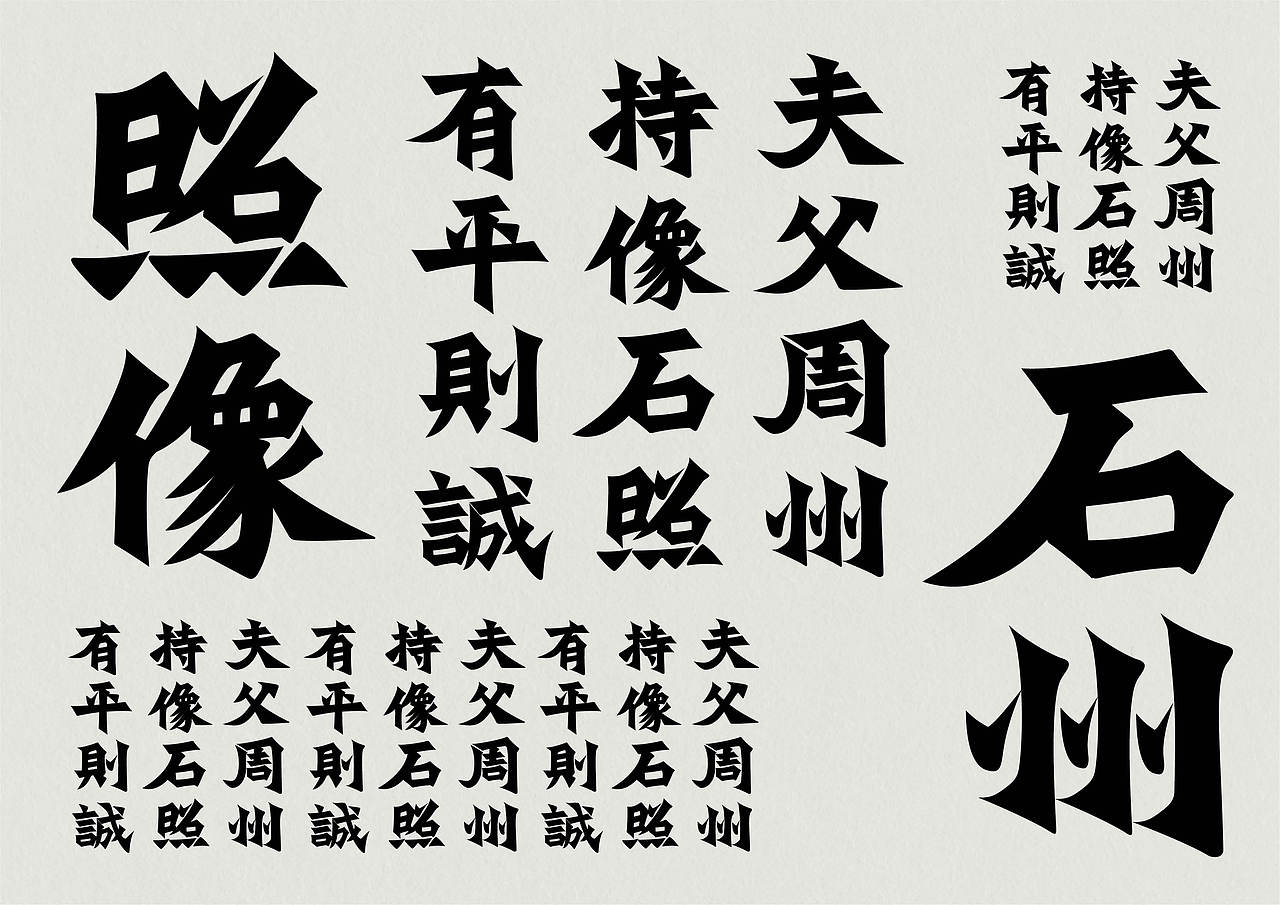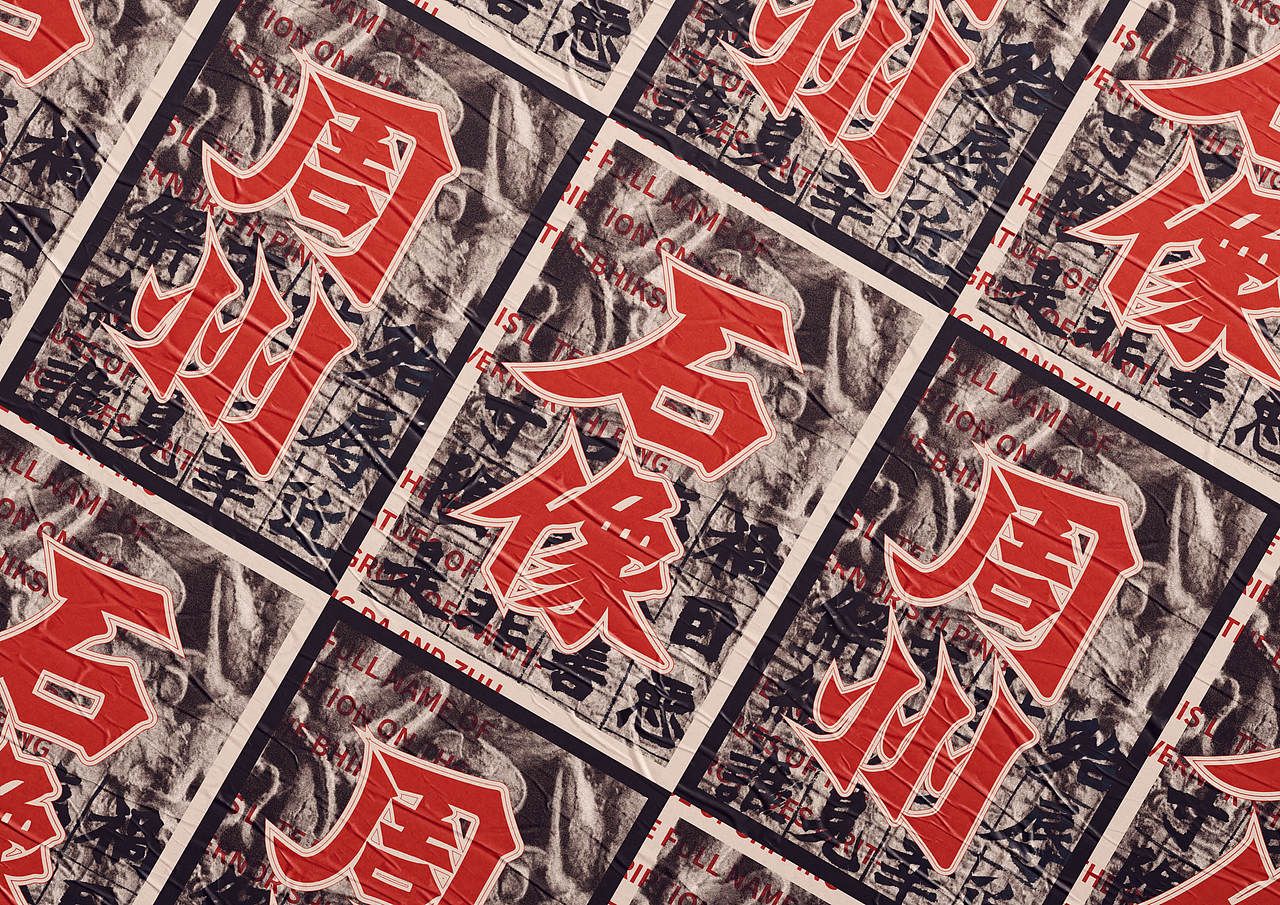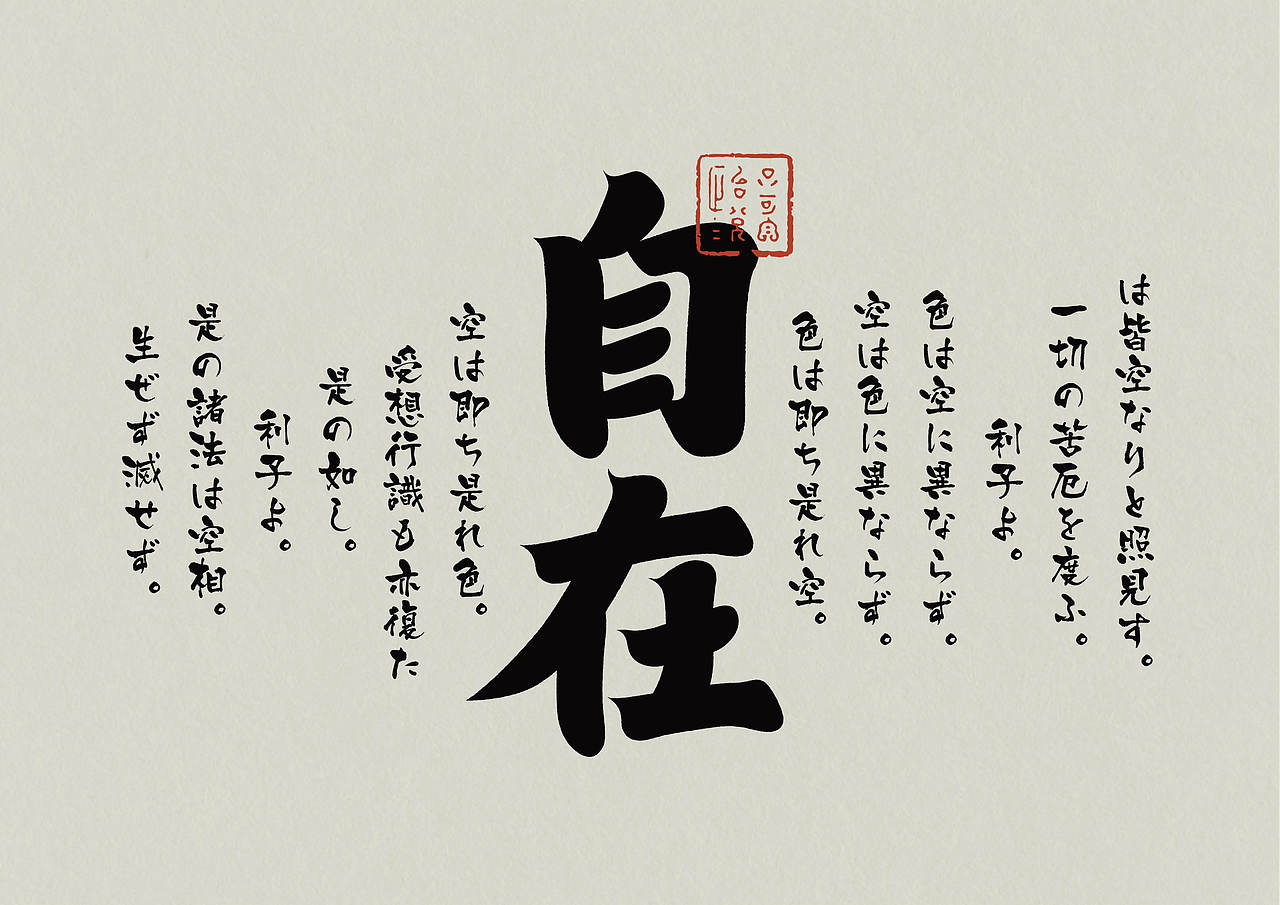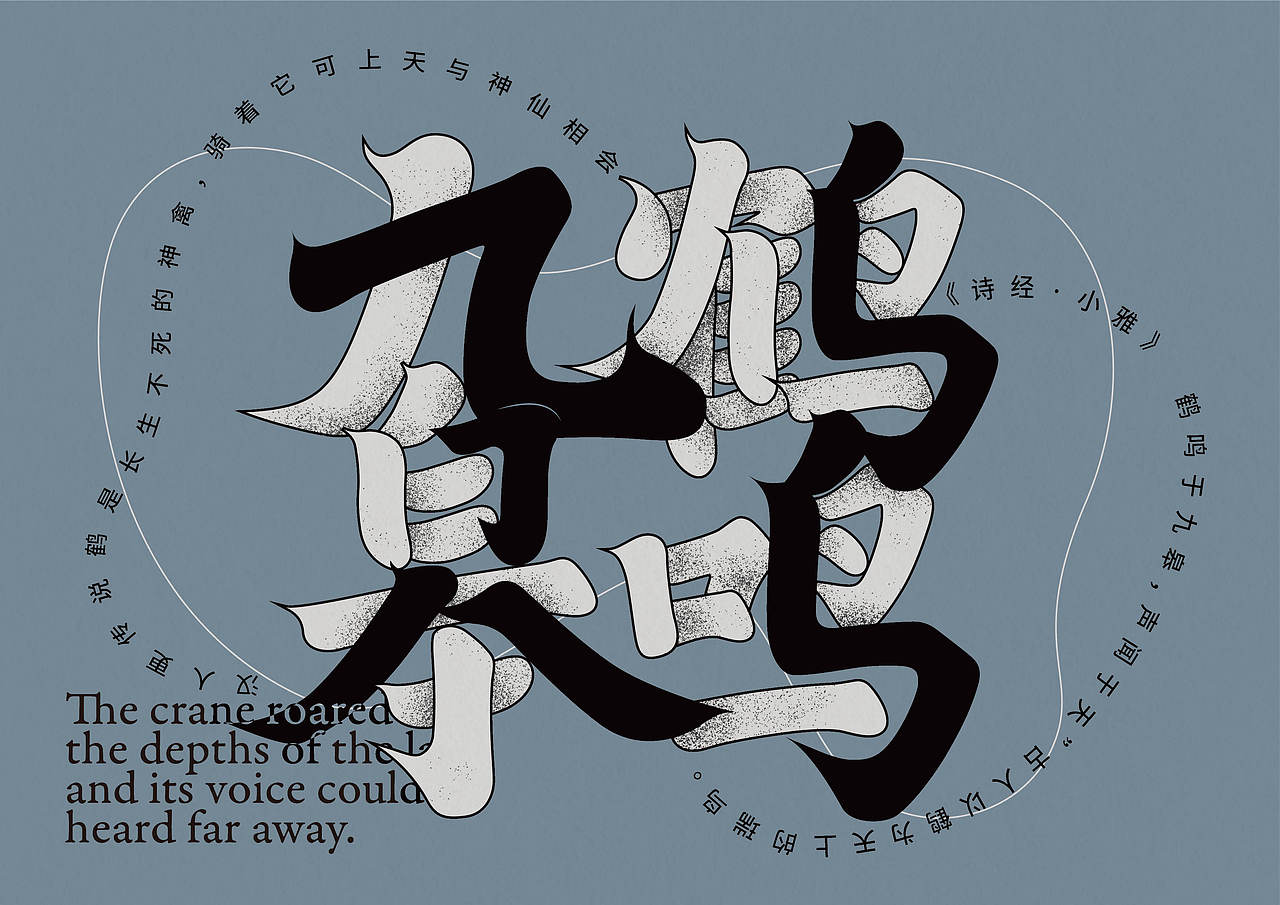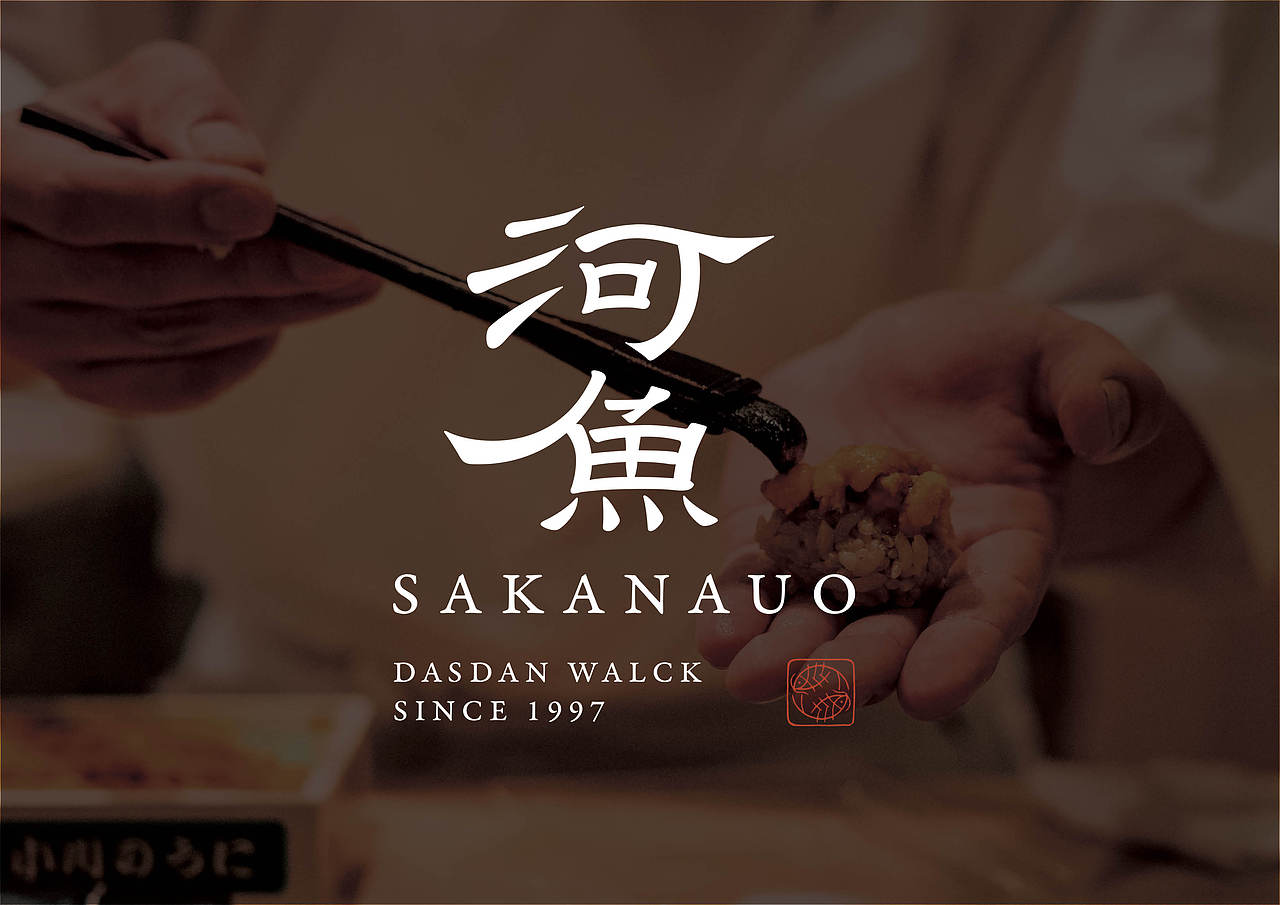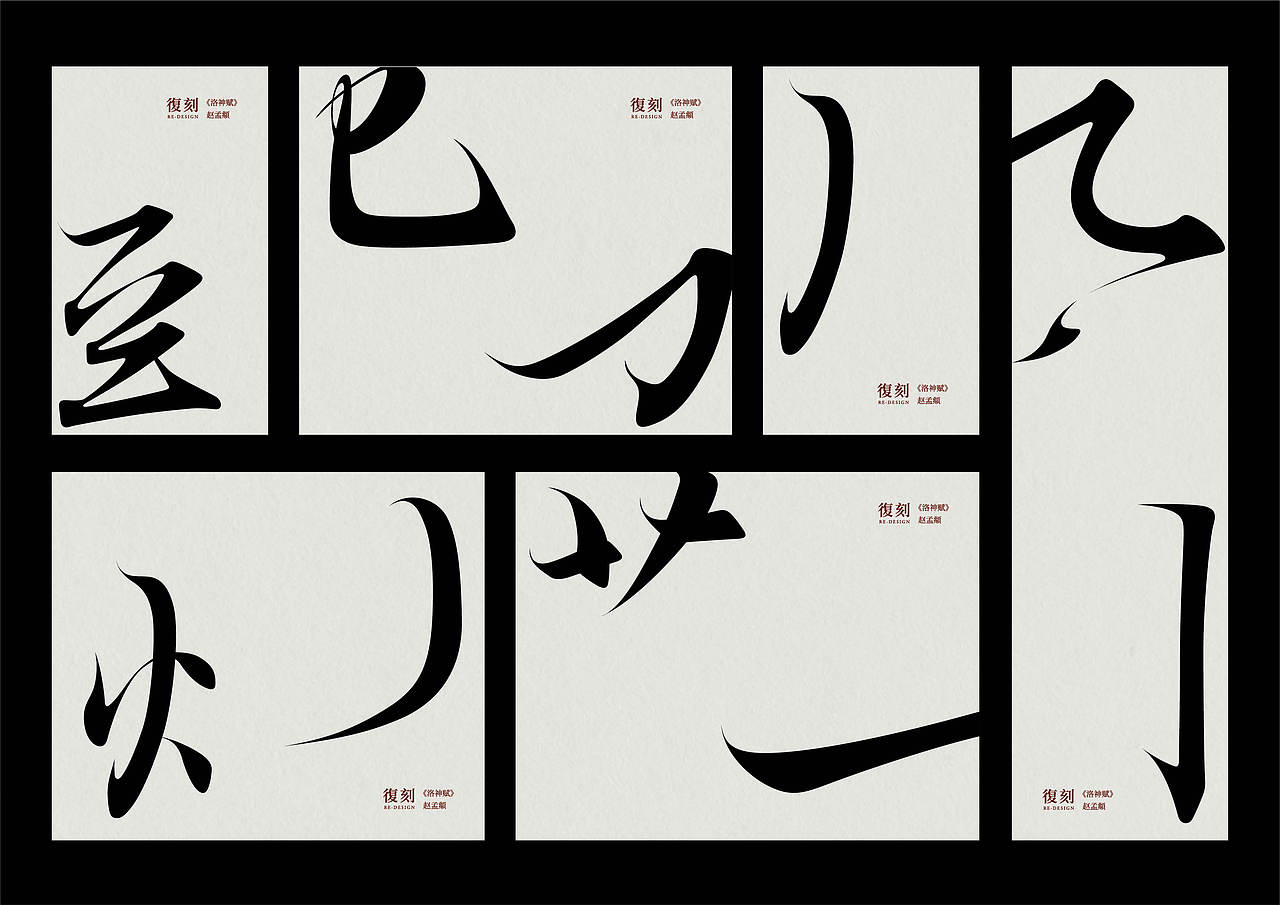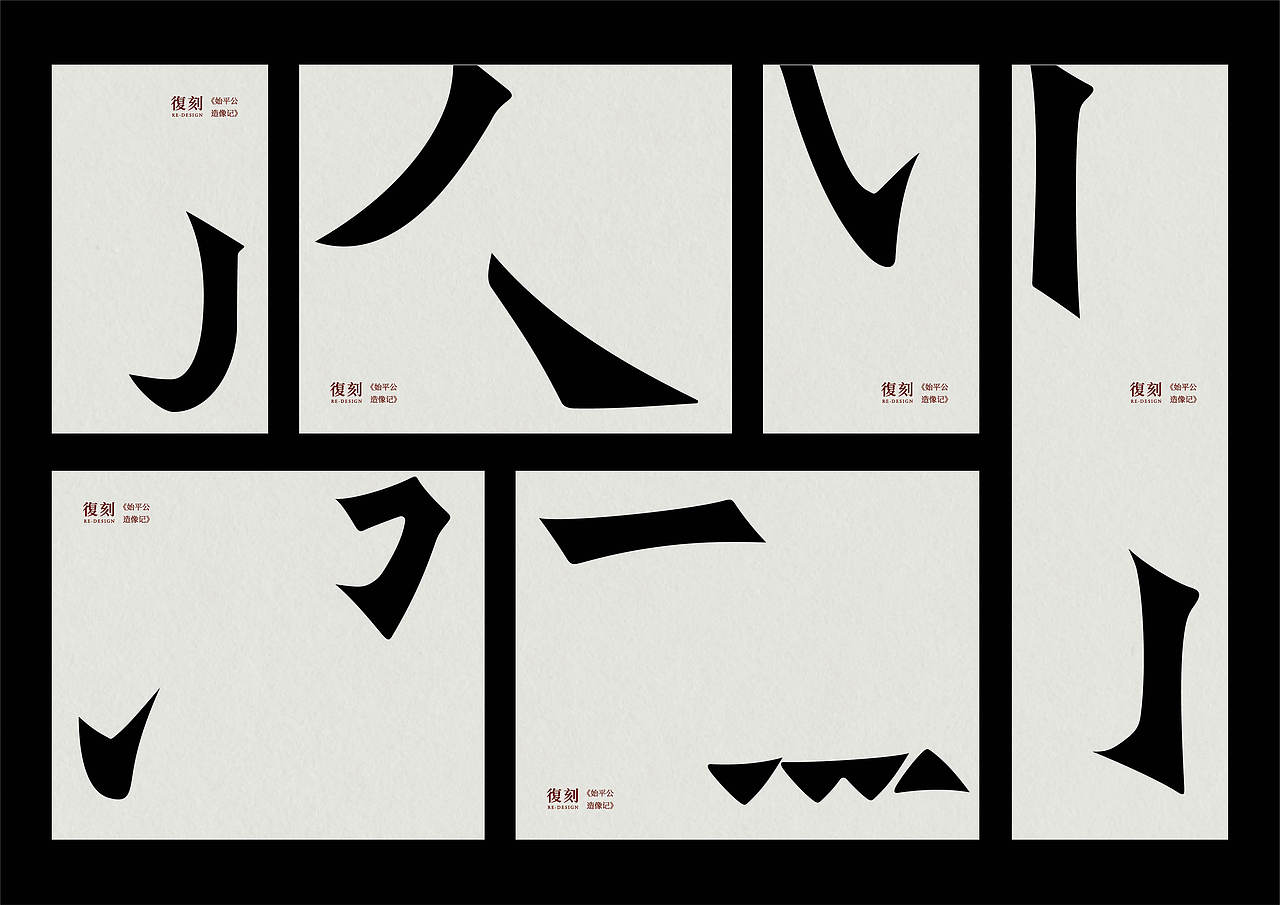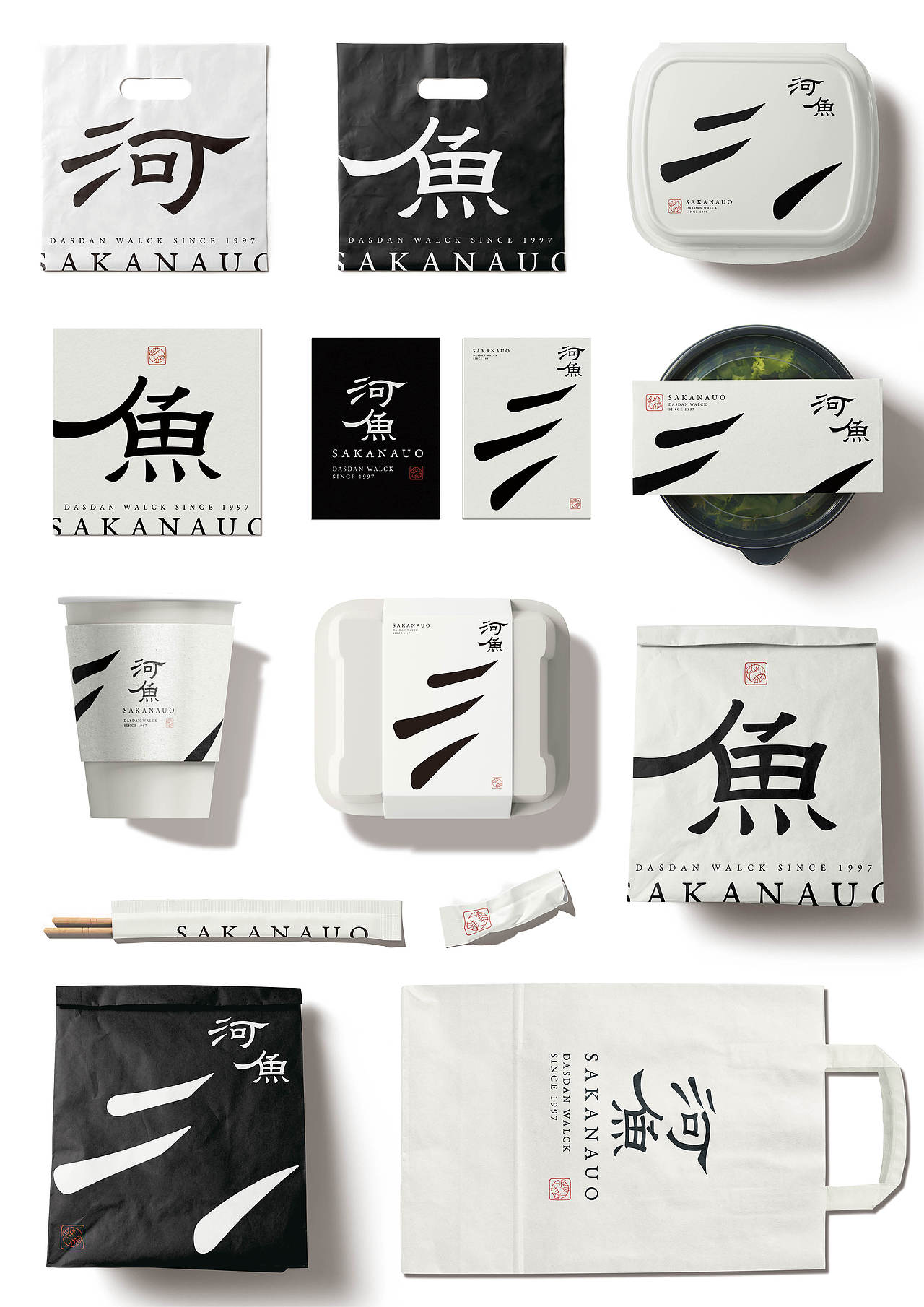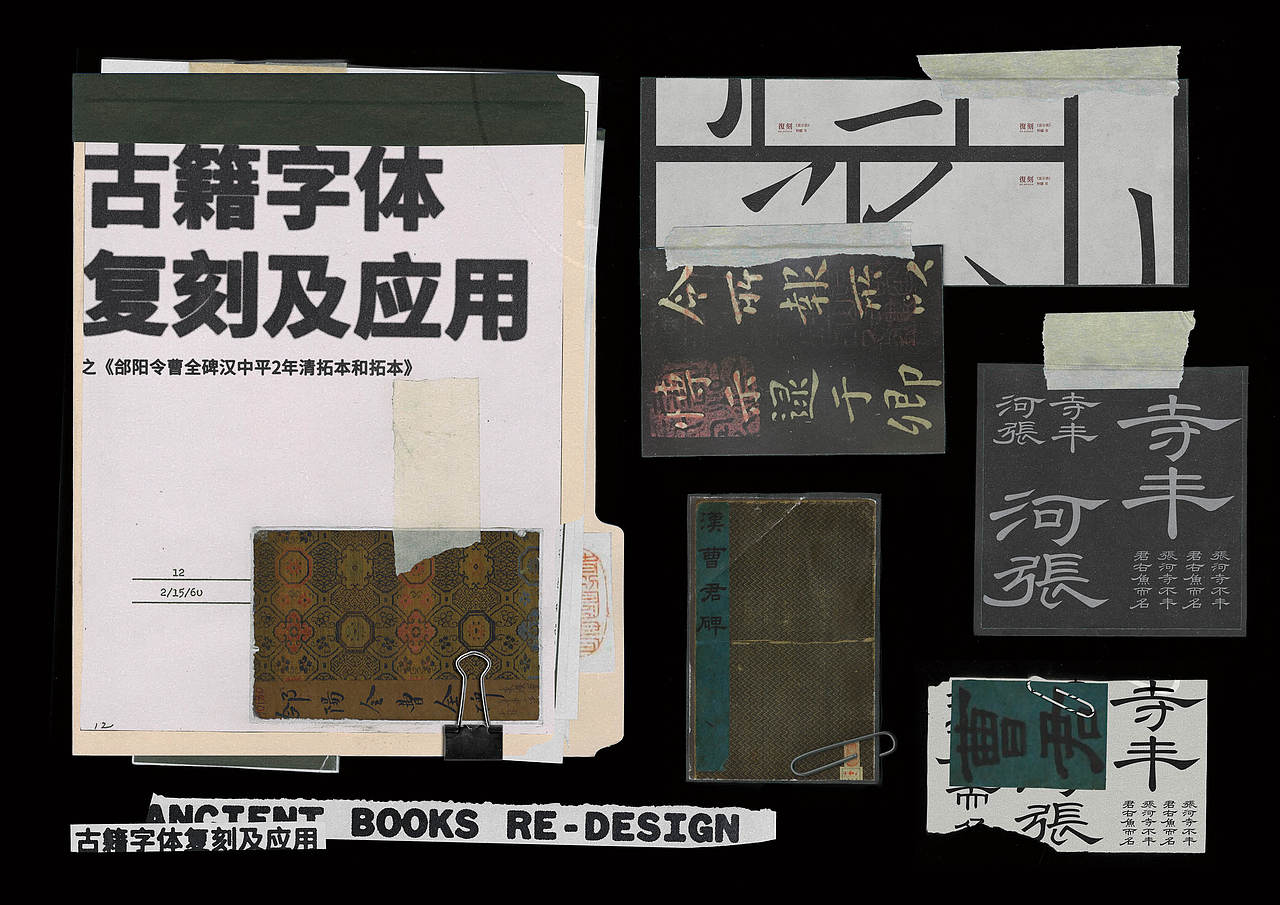
书法汉字复刻及字体应用
复刻-穿越时空的文字对话
中国的传统艺术——“琴棋书画”、“诗书画印”,“书”早已成为国人心中极高的艺术。文字不止是传达信息的媒介,在信息之外,还包含着一层言外之意,那是书者通过自身独特的文字视觉形式,传达的情感和意境。与其他视觉艺术不同的是,书法几乎没有色彩,没有具象的图形,没有材质的堆叠,在极简的黑与白之间,创造出独特的美感。大多中文字自身就是表意的,文字造型和意义相关联,本身就有一种情感价值。加上书法家对笔法、结构、章法的个性处理,又为文字加上了一层意境。
这就是为什么要复刻碑帖的缘由,我们很难凭空创造出富有美感的字型。荀子在《劝学》里说过:“君子性非异也,善假于物也。”借助复刻的方式,取法乎上,学习历代书法的经验,是一条行之有效的捷径。复刻的时候可以主要关注四个维度,即笔法、结构、章法、意境。前三者是技法层面的,唯有纯熟的技法才能表现出字的意境以及背后的情感和个性。复刻的时候可以先整体地感受,用几个关键词形容它的意境(或者说个性和气质),然后再从笔法、结构、章法层面去细节地看和分析,这些技法如何表现了这种意境。
这个作品集合了7本古籍字体复刻,以及其字体运用场景。